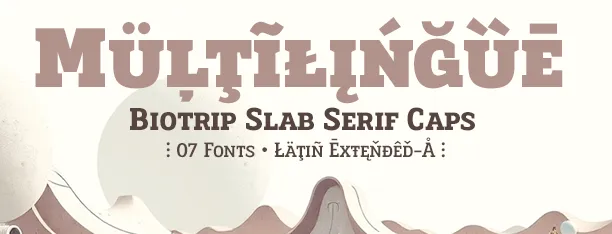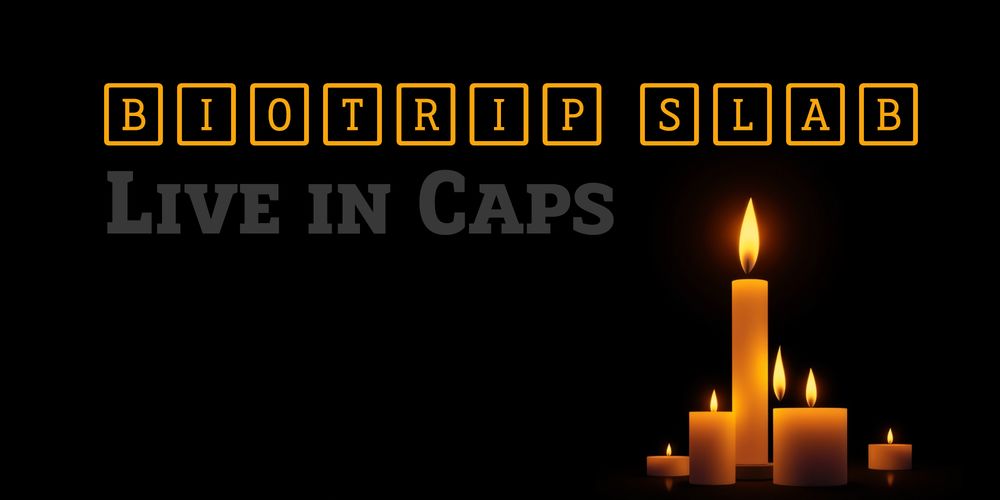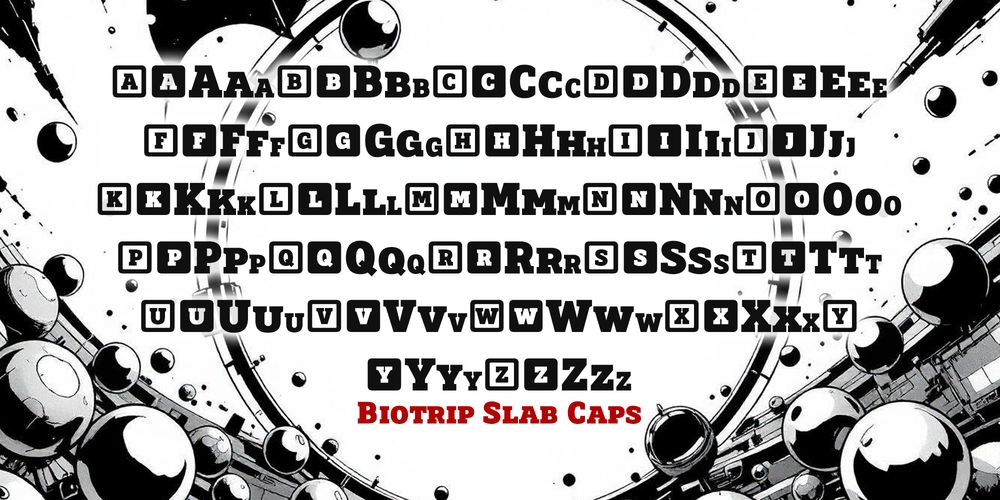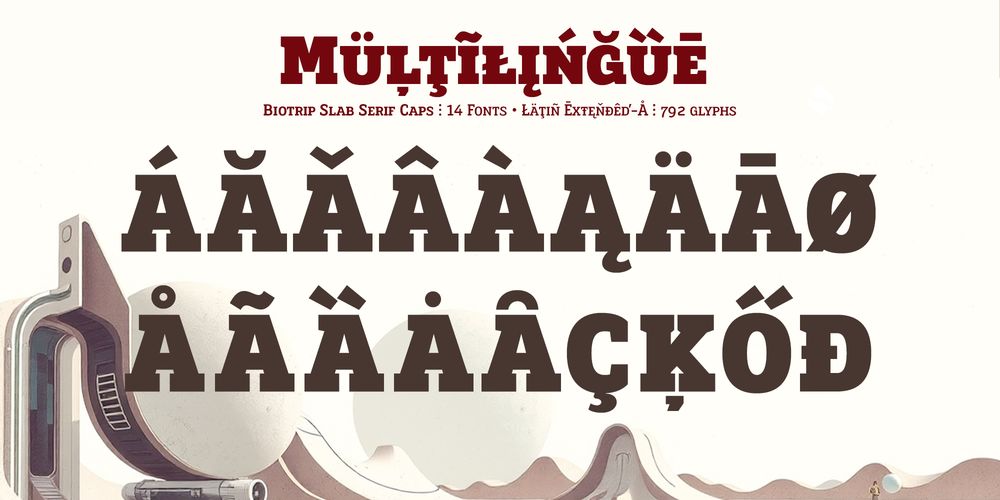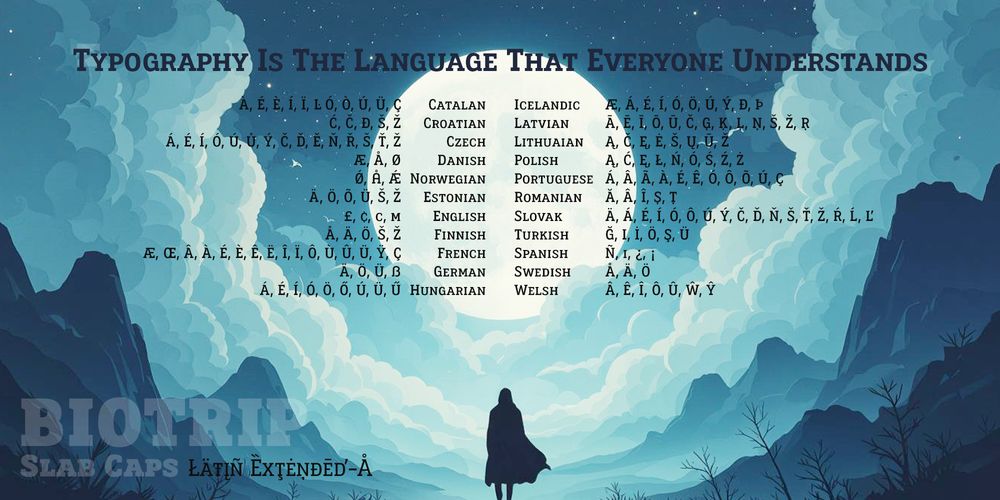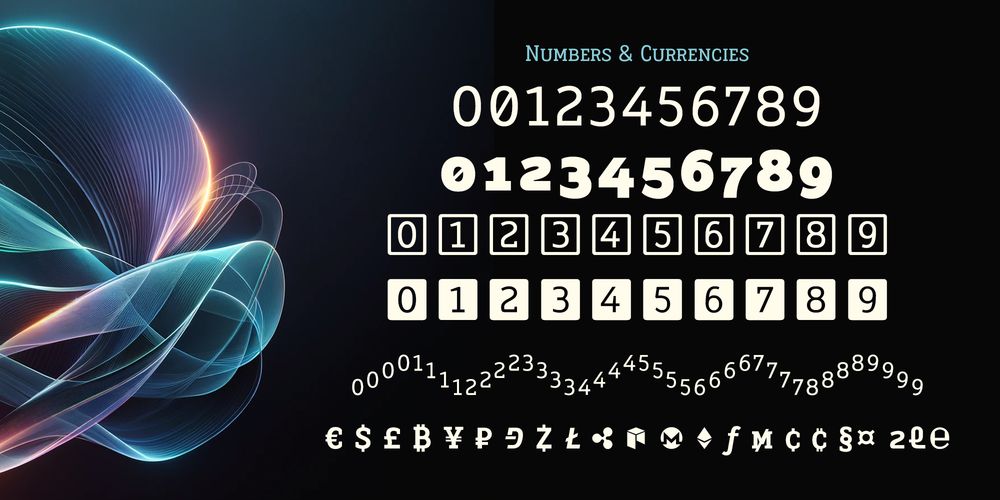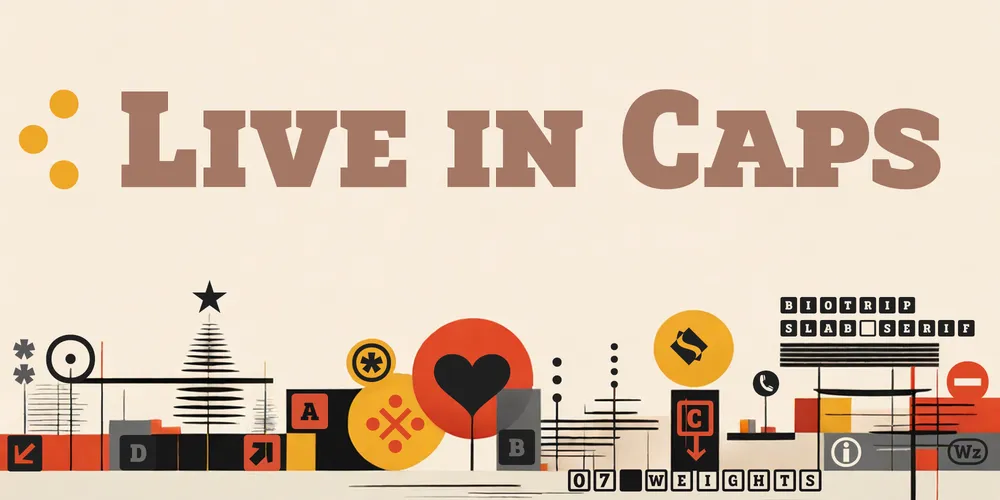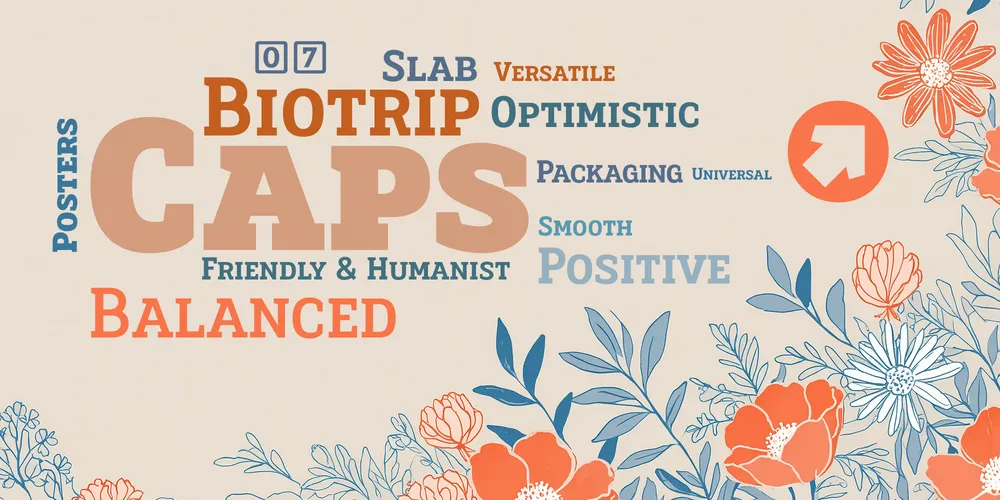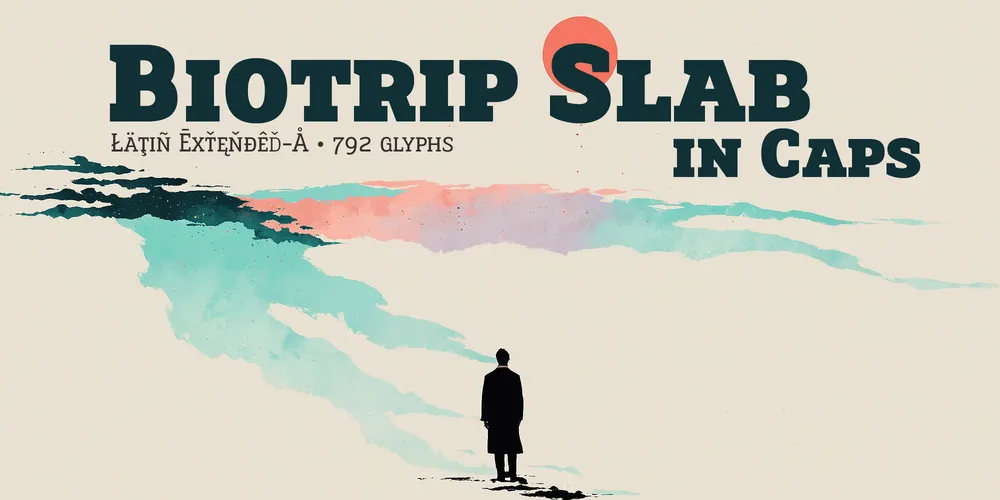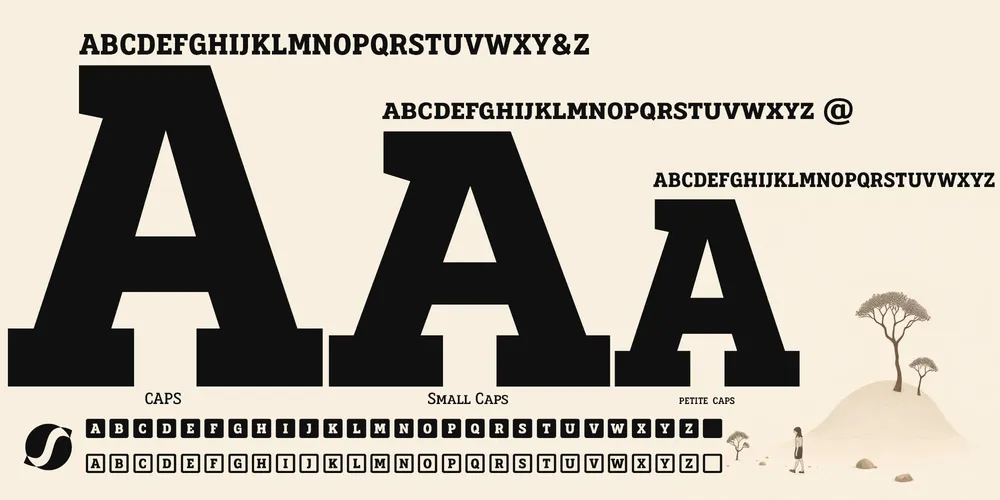
Estilo: Slab Serif, Display, Humanist, Capitals, Small Caps, Petite Caps
802 glyphs w/ 181 alternates: Numbers & Letters
Tipografía Slab Serif en versalitas
Siempre me ha intrigado el equilibrio silencioso de las versalitas. No buscan imponerse como las mayúsculas monumentales, ni desaparecer como las minúsculas en el flujo del texto. Habitan un territorio intermedio: un espacio de precisión, de ritmo y de equilibrio tipográfico. Con esa idea nace Biotrip Serif Caps, la versión en versalitas y mayúsculas de Biotrip Serif, una extensión natural dentro del Universo Biotrip. Este es un viaje que comenzó con la Sans, y encontró su peso y carácter en la Serif.
Biotrip Serif Caps no es una simple versión en mayúsculas de su predecesora; conserva el espíritu estructural de Biotrip Serif —su equilibrio entre geometría, modulación orgánica y presencia editorial— pero lo traslada a un lenguaje más concentrado y horizontal. Las proporciones se ajustan, el ritmo se vuelve más compacto y la textura tipográfica adquiere una elegancia silenciosa. Es, en esencia, la misma voz, pero hablada desde otra escala del lenguaje tipográfico: la de las versalitas, donde la estructura se vuelve más consciente y el diseño revela su arquitectura interior.
Las Small Caps serifadas tienen una historia de poder. En la tradición editorial clásica, se usaban para acrónimos, para citas elegantes, para crear jerarquías sin el grito visual de las mayúsculas completas. Nacidas en la tradición de los manuscritos y perfeccionadas durante el auge de la imprenta, las letras mayúsculas de caja alta siempre han ocupado un lugar especial en la jerarquía visual del texto.
Las fuentes en mayúsculas (especialmente las versalitas bien diseñadas) poseen una cualidad única: son a la vez monumentales y discretas. Construyen un texto con la solidez de una inscripción lapidaria, pero sin el grito de las mayúsculas tradicionales. Siempre que se diseñen cuidadosamente —no como simples reducciones de mayúsculas, sino como caracteres construidos específicamente para su tamaño— generarán un ritmo tipográfico extraordinariamente refinado. Usarlas bien es un arte.
El resultado es una familia humanista, slab serif y geométrica, donde la solidez de las serifas egipcias convive con una modulación orgánica. Aunque parte de una estructura racional, sus formas no son rígidas: respiran. Las curvas fluyen con naturalidad, las aperturas son generosas y la textura del texto se mantiene clara incluso en tamaños pequeños. Sus formas, abiertas y amables, crean una presencia fuerte sin resultar intimidantes. Son letras que invitan a ser leídas, incluso en condiciones exigentes. Esa legibilidad excepcional no es accidental: es el resultado de cientos de decisiones conscientes sobre óptica, peso y ritmo.
Biotrip Slab Serif Caps es una tipografía multipropósito diseñada con extremo cuidado para ofrecer legibilidad, equilibrio y carácter. La familia incluye 07 Pesos —Light, Regular, Medium, Semi Bold, Bold, Extra Bold y Black— que permiten construir jerarquías sólidas sin perder coherencia visual. Desde la elegancia contenida del Light hasta la presencia rotunda e inapelable del Black. Cada peso es un matiz, una inflexión de esa misma voz mayestática.
Cada peso mantiene la tensión geométrica de Biotrip Serif —esa combinación única de serifas slab en la base y serifas lapidarias en la parte superior—. El resultado es una tipografía que pesa, que tiene presencia física, pero que nunca pierde la calidez orgánica.
Un Motor de Precisión: El Universo OpenType
Como creador, me obsesionan los detalles. Quería que Biotrip Serif Caps fuera una herramienta total, un ecosistema donde la estética y la utilidad conviven en perfecta armonía existencial:
- Jerarquía Infinita: Con 03 juegos de Mayúsculas y 05 juegos de minúsculas (petite caps), pensados para crear sistemas editoriales precisos y flexibles.
- Matemática y Poesía: He incluido 08 juegos completos de números y funciones posicionales (ordinales, numeradores, denominadores e inferiores científicos). Porque incluso una fórmula matemática merece ser hermosa.
- Puntuación con Alma: ¿Por qué conformarse con lo básico? He añadido signos decorativos que evocan la mística de la imprenta clásica: Tricolon, referencemark, asterism, therefore, because… detalles que cuentan una historia por sí solos.
- Anotación y Simbología: Formas de anotación alternativas en dos estilos, flechas y un soporte global de divisas que abraza desde lo tradicional hasta el futuro de las criptomonedas.
- Señalización e inscripciones: Su legibilidad y peso visual la hacen perfecta para placas, rótulos y sistemas de orientación que buscan permanencia.
- Packaging Premium: Para productos que quieran comunicar calidad, tradición y refinamiento a través de la tipografía.
Biotrip Serif Caps es mi respuesta creativa a la necesidad de estructura en un mundo fluido. Es geometría con pulso, es respeto por la tradición y es, sobre todo, una herramienta para que tus ideas dejen una huella imborrable.